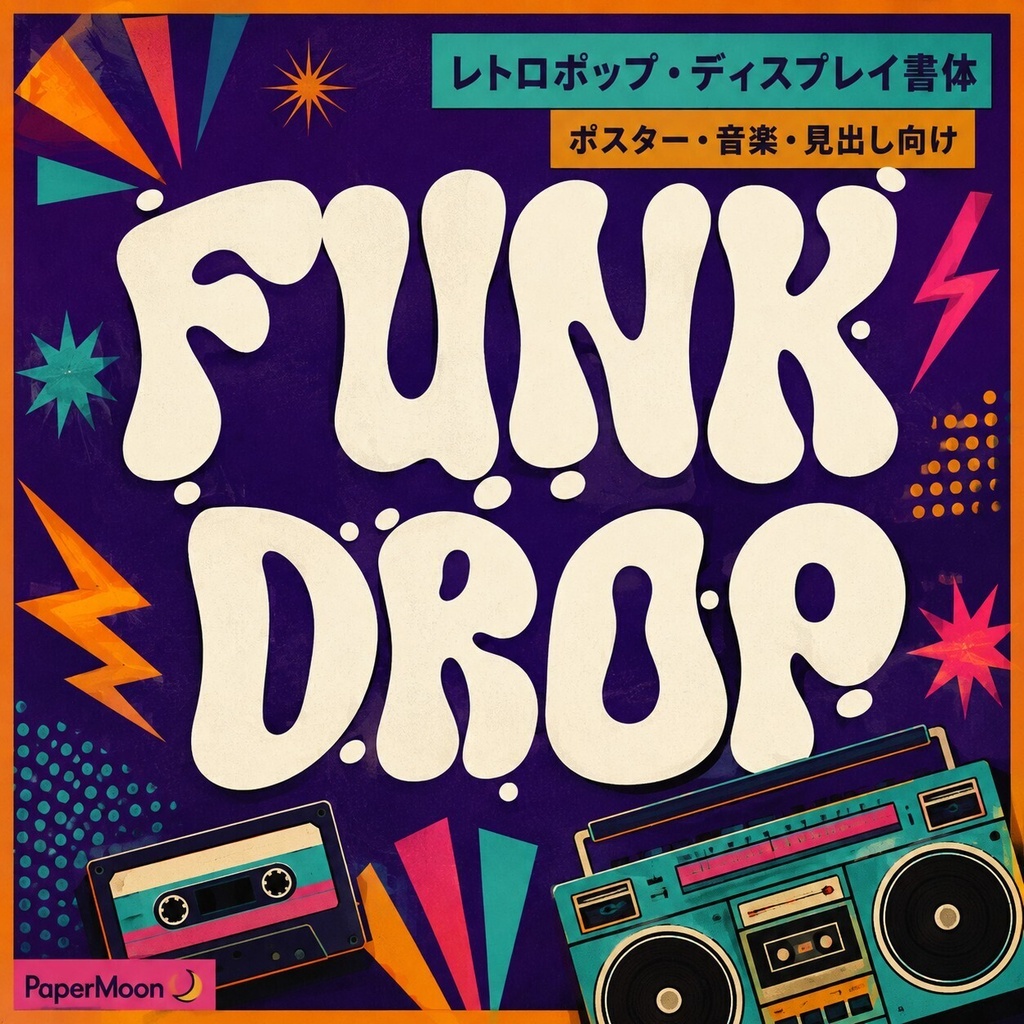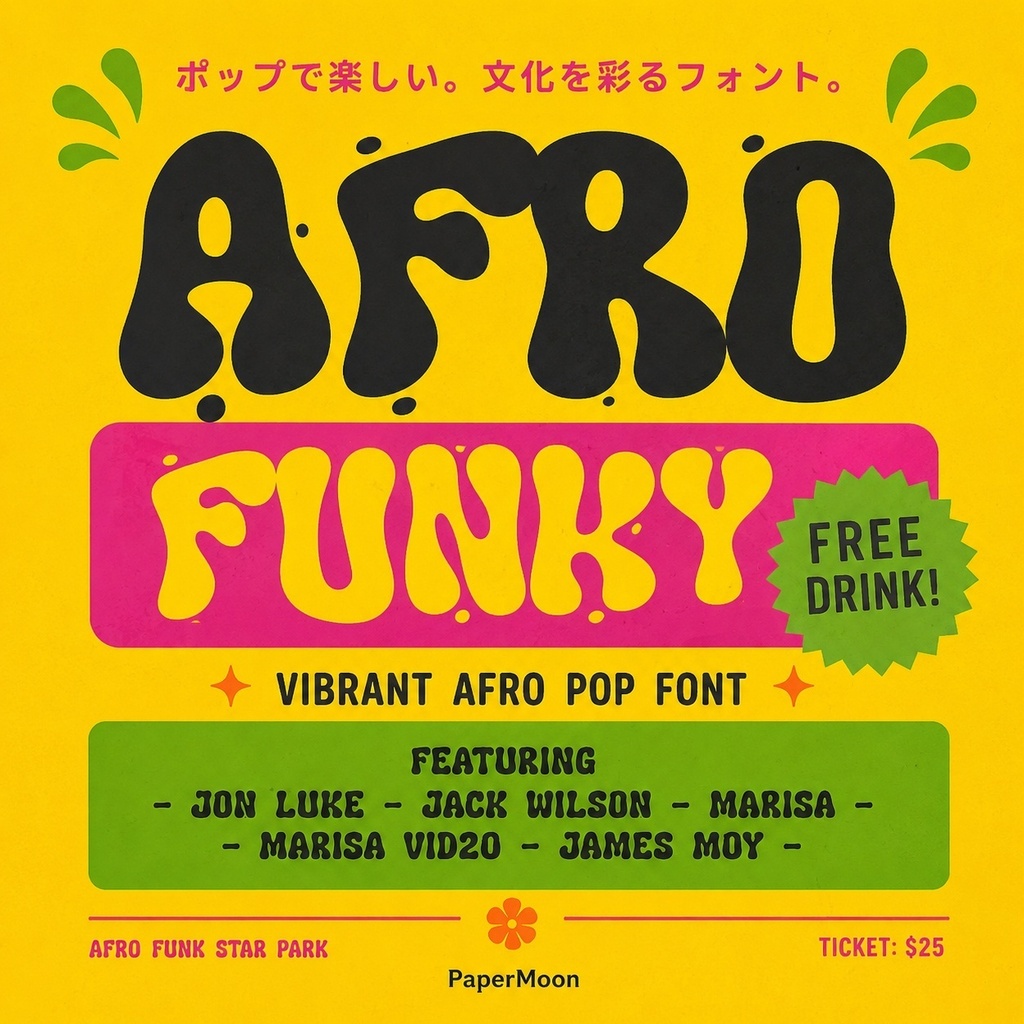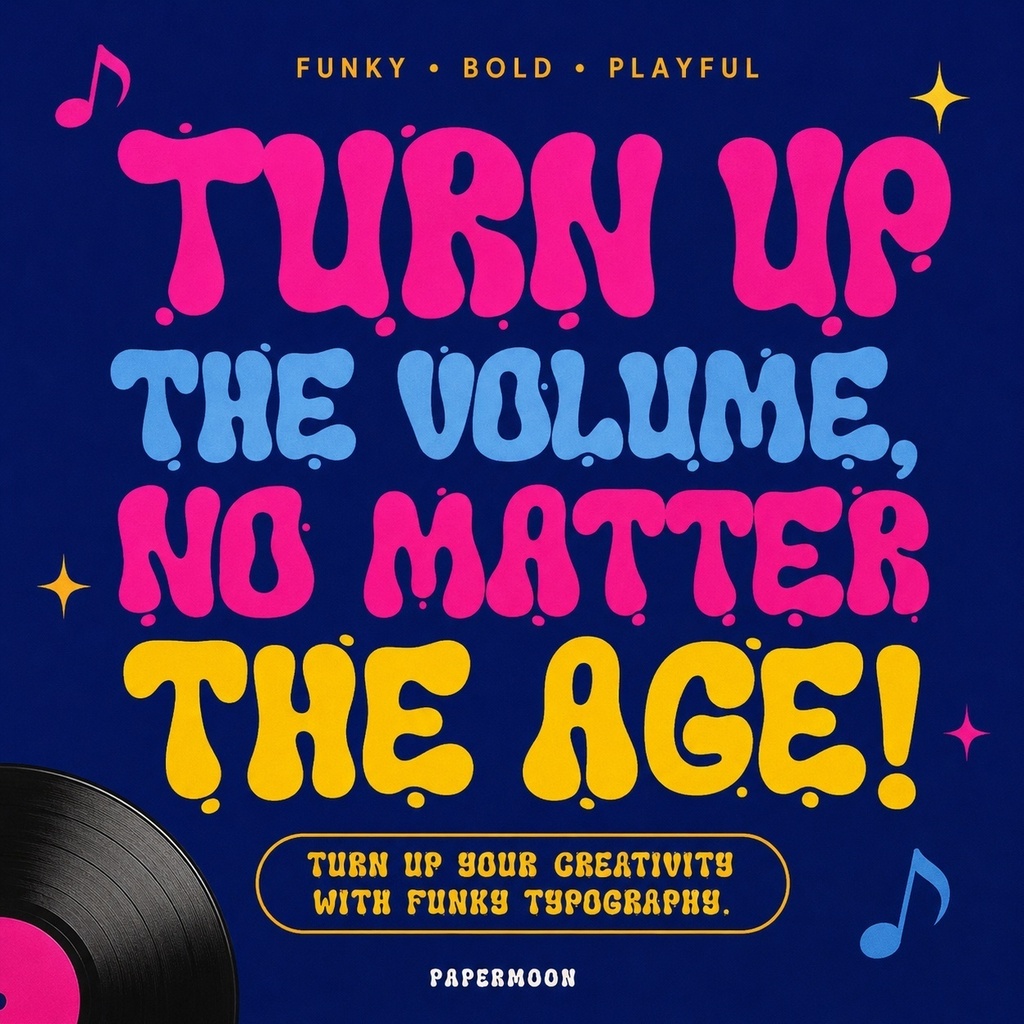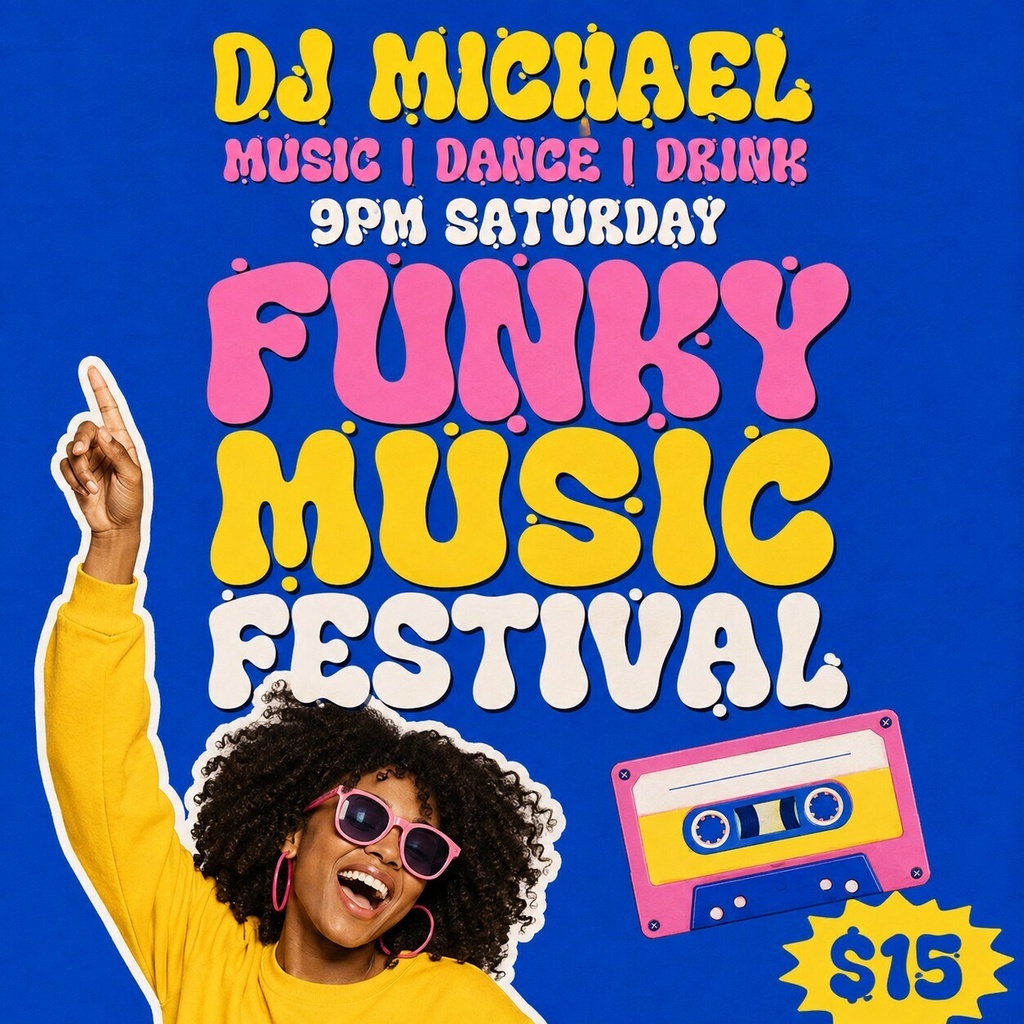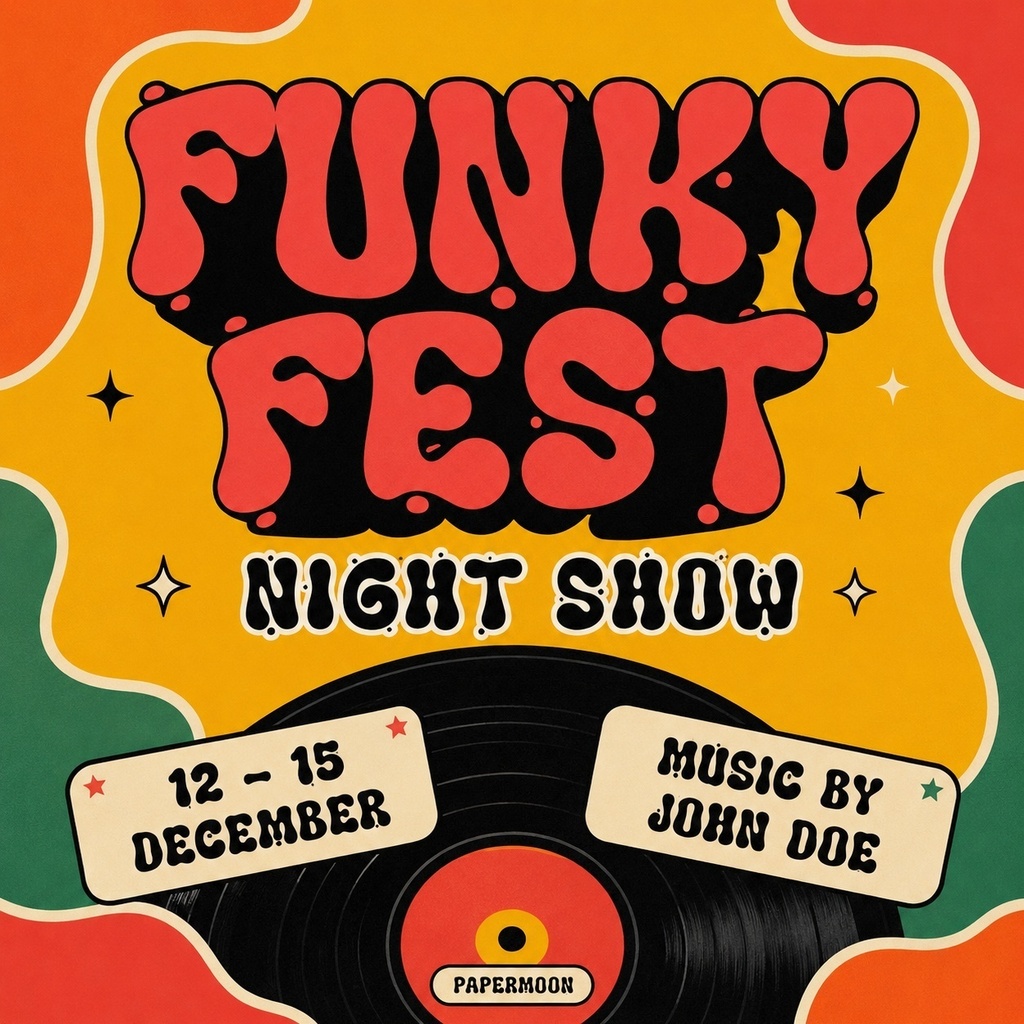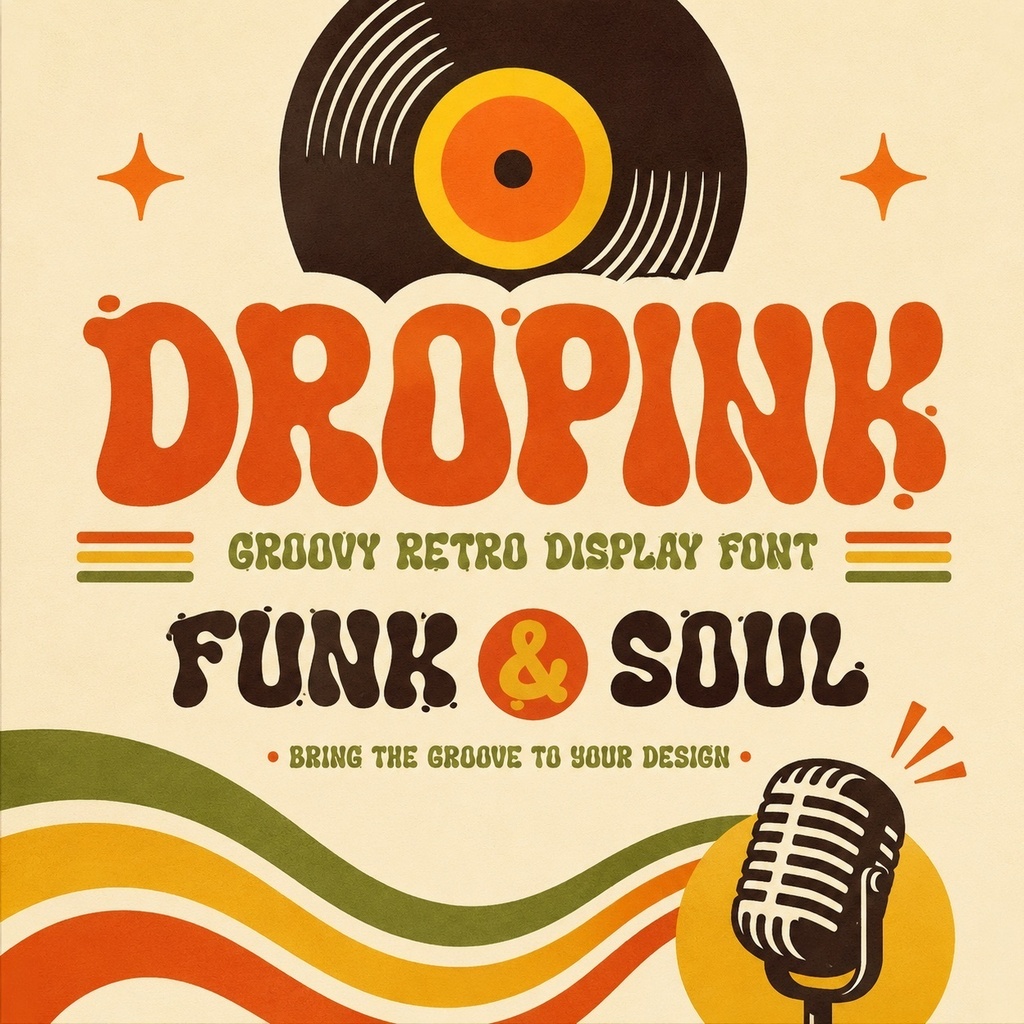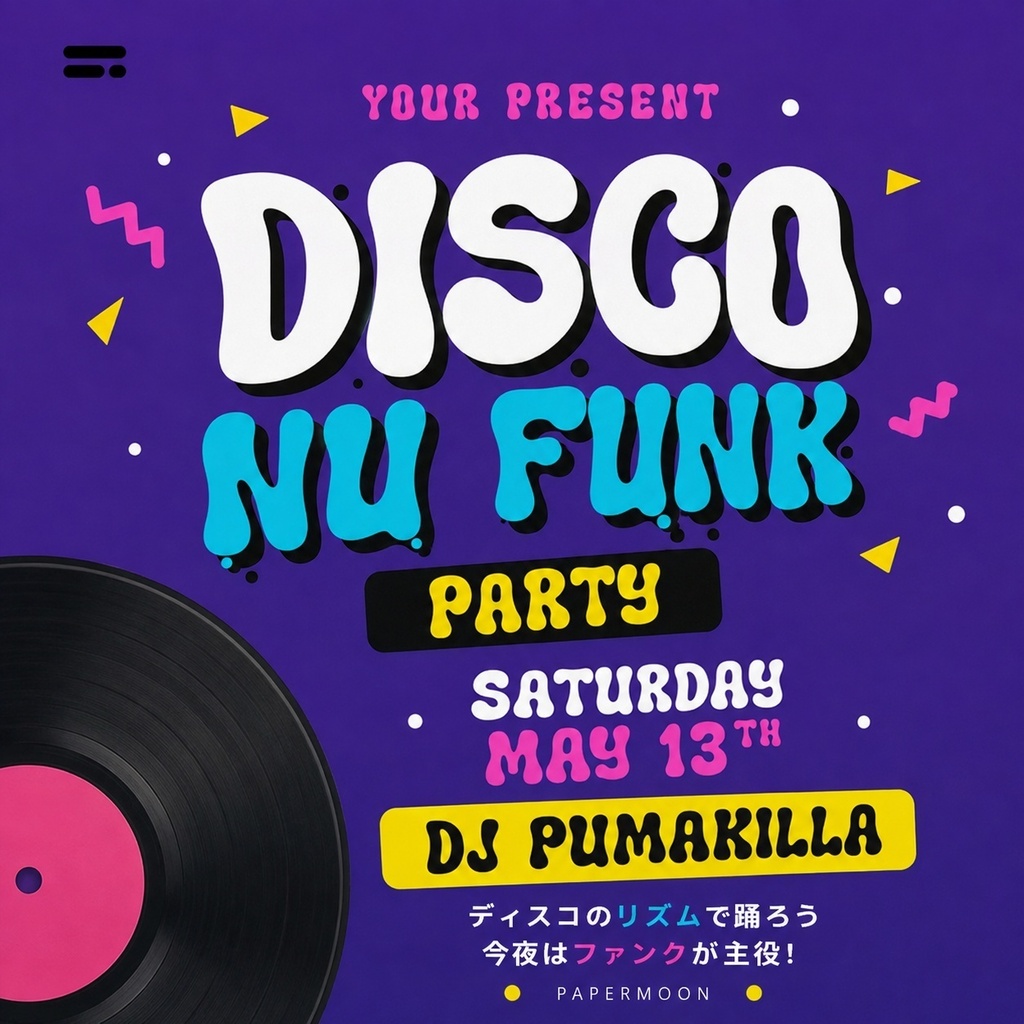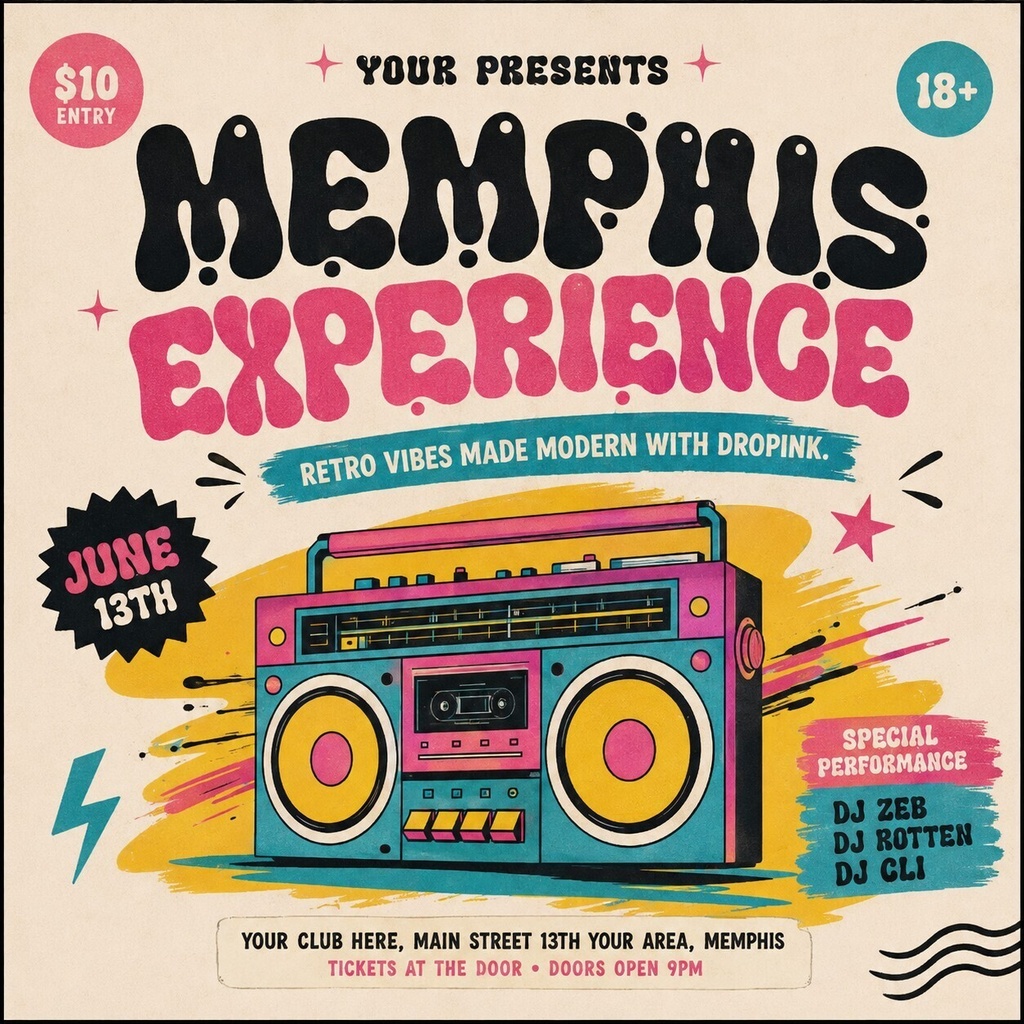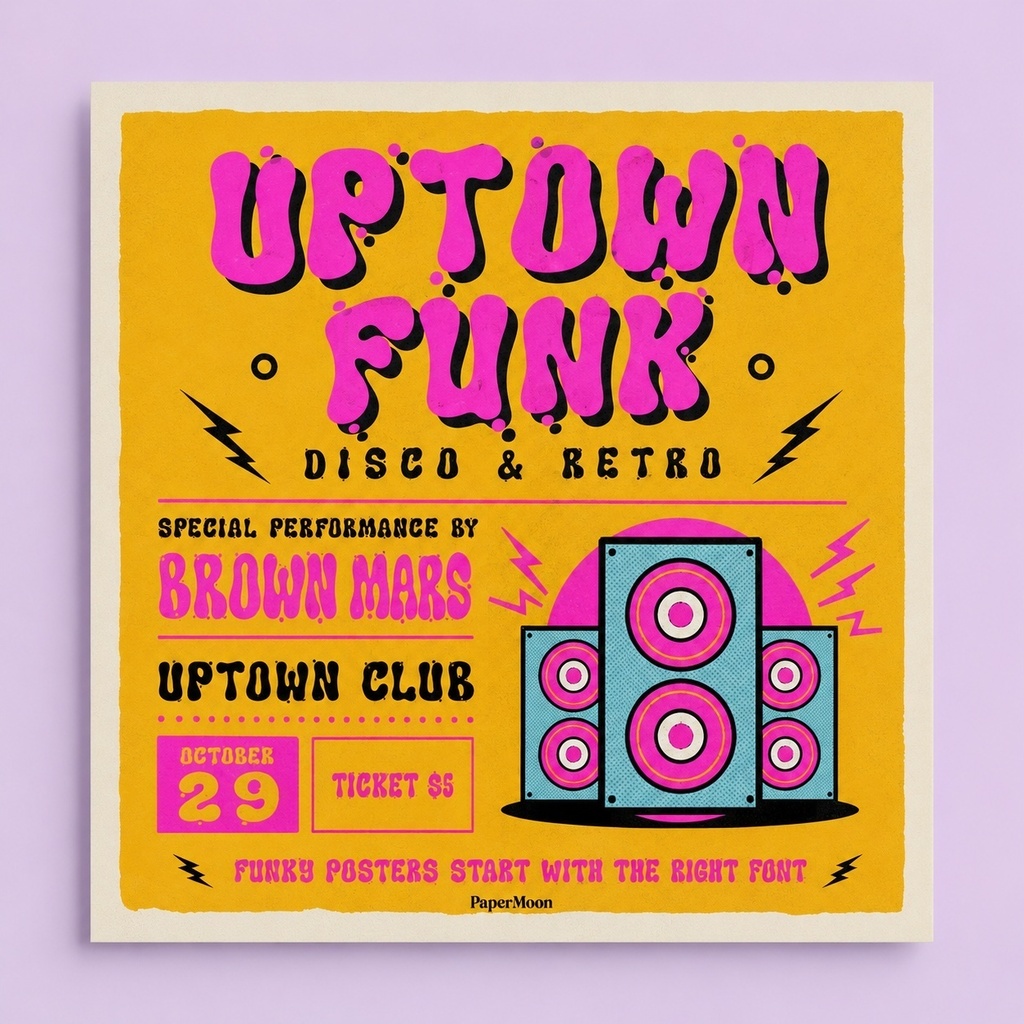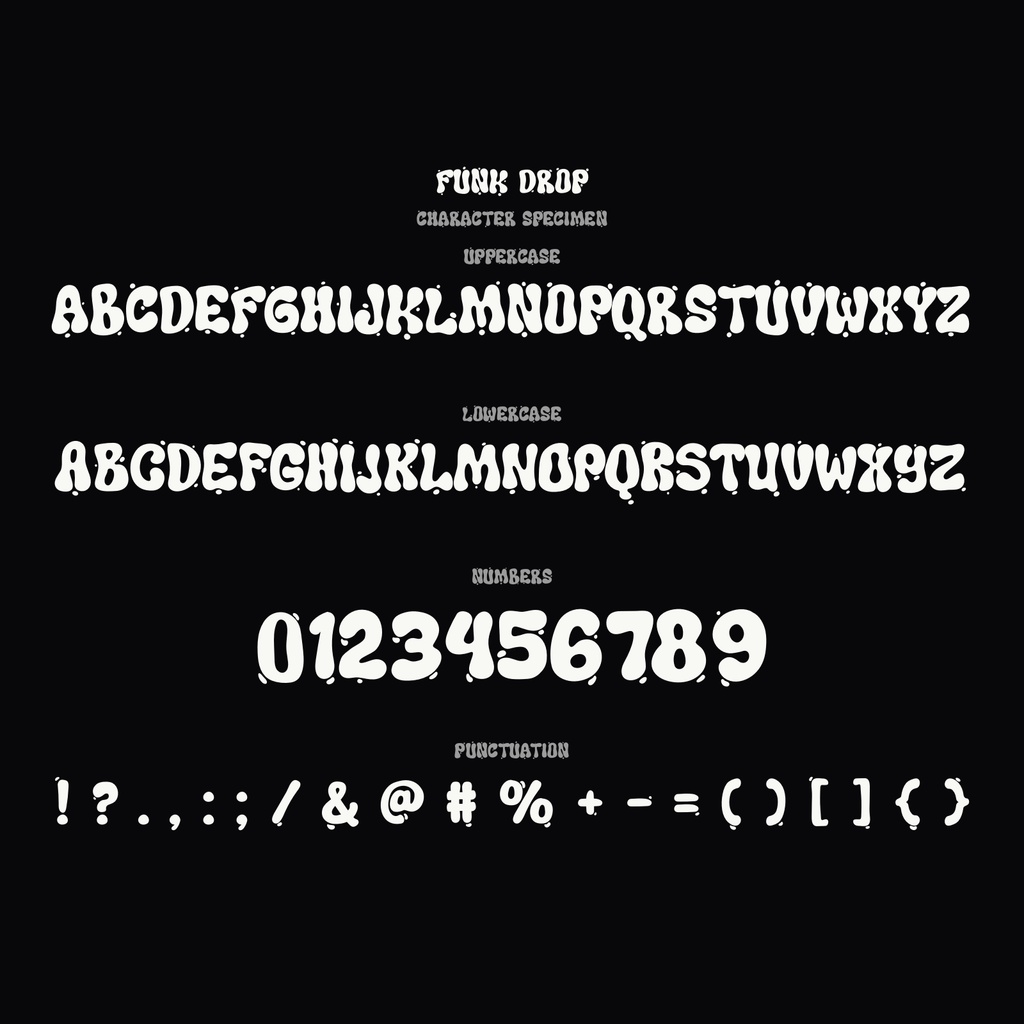
Funk Drop | 音楽向けディスプレイ英字フォント | ロゴ・ポスター・配信
Funk Dropは、音楽のエネルギーとリズムから着想を得た、太く表情豊かなディスプレイ英字フォントです。動きのある文字のかたちが、見出しやタイトルに力強いアクセントを加えます。 コンサート、フェス、ライブイベントのポスターやフライヤー、アルバムカバー、バンドロゴ、Tシャツ・キャップ・ポスターなどの音楽グッズにおすすめです。プレイリストカバー、バナー、配信プロモーション、音楽スクールの教材、オーディオ機器やレコードショップの広告など、音楽を軸にした制作物で印象的な文字組みを作れます。 収録内容 ・OTF、TTF、WOFF ・大文字 A–Z、小文字 a–z、数字、句読点・記号 ・PC / Mac向けフォントデータ ・追加のデザインソフトを必要とせず利用できるPUAエンコード文字 対応文字 ・欧文基本文字セット(Latin) ・日本語、キリル文字、ギリシャ文字は収録していません 用途 ・コンサート、フェス、ライブのポスター・フライヤー ・アルバムカバー、バンドロゴ、音楽ブランド ・Tシャツ、キャップ、ポスターなどのグッズ ・プレイリストカバー、バナー、配信プロモーション ・音楽スクール、学習教材 ・オーディオ機器、レコードショップ、音楽関連広告 形式 ・OTF(OpenType) ・TTF(TrueType) ・WOFF(Webフォント) 対応環境 ・Windows / macOS ・Adobe Illustrator、Photoshop、InDesign、Microsoft Word ・通常のフォントとしてインストールして使用できます ・PUAエンコード文字は追加のデザインソフトなしで利用できます 利用許諾 ・商用利用と個人利用の2種類のバリアントを用意しています。各バリアントの許諾条件は販売時に設定する利用規約に従ってください。 ・フォントデータそのものの再配布・再販売・共有はできません。その他の利用条件は販売時の許諾文をご確認ください。